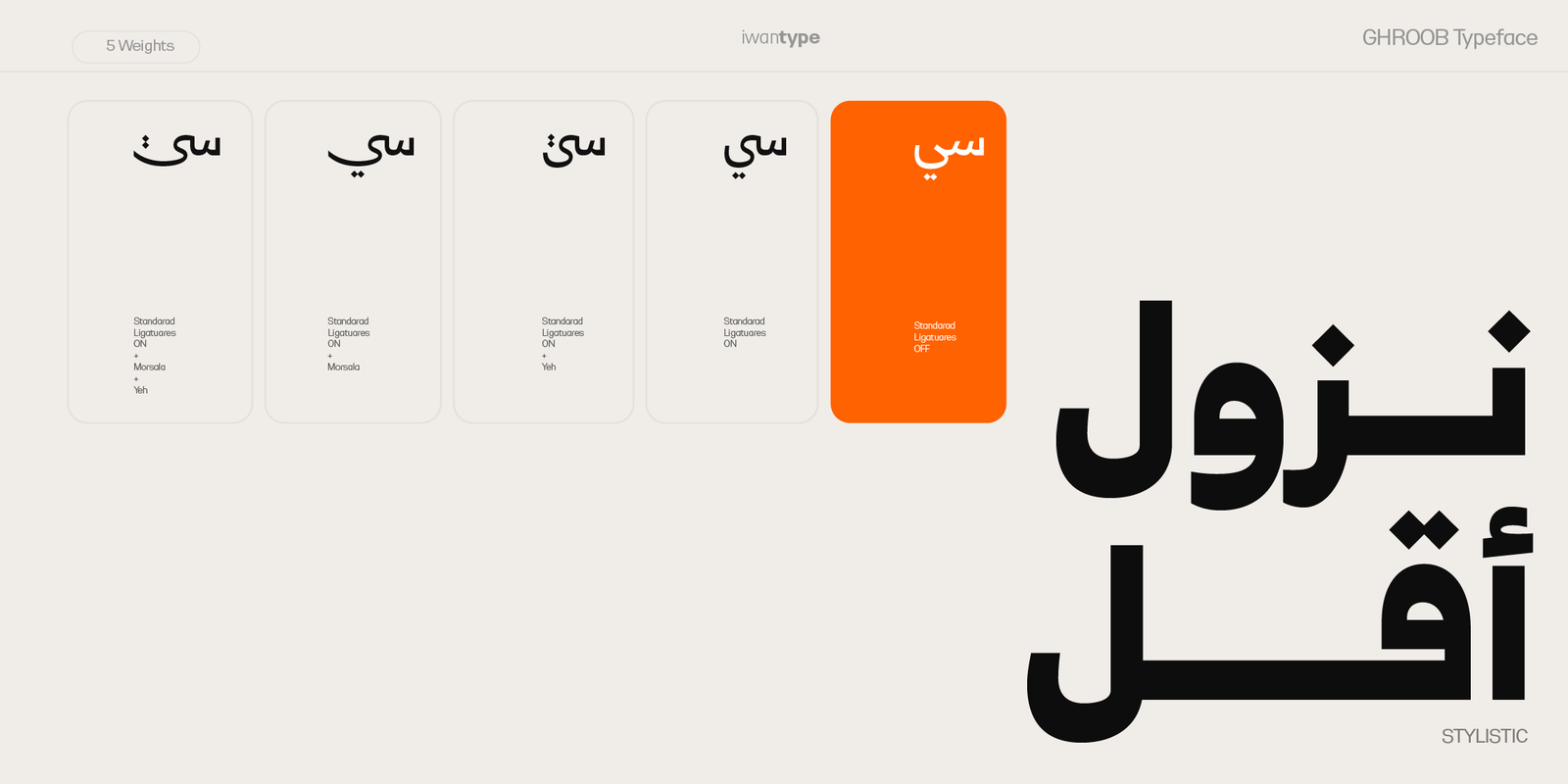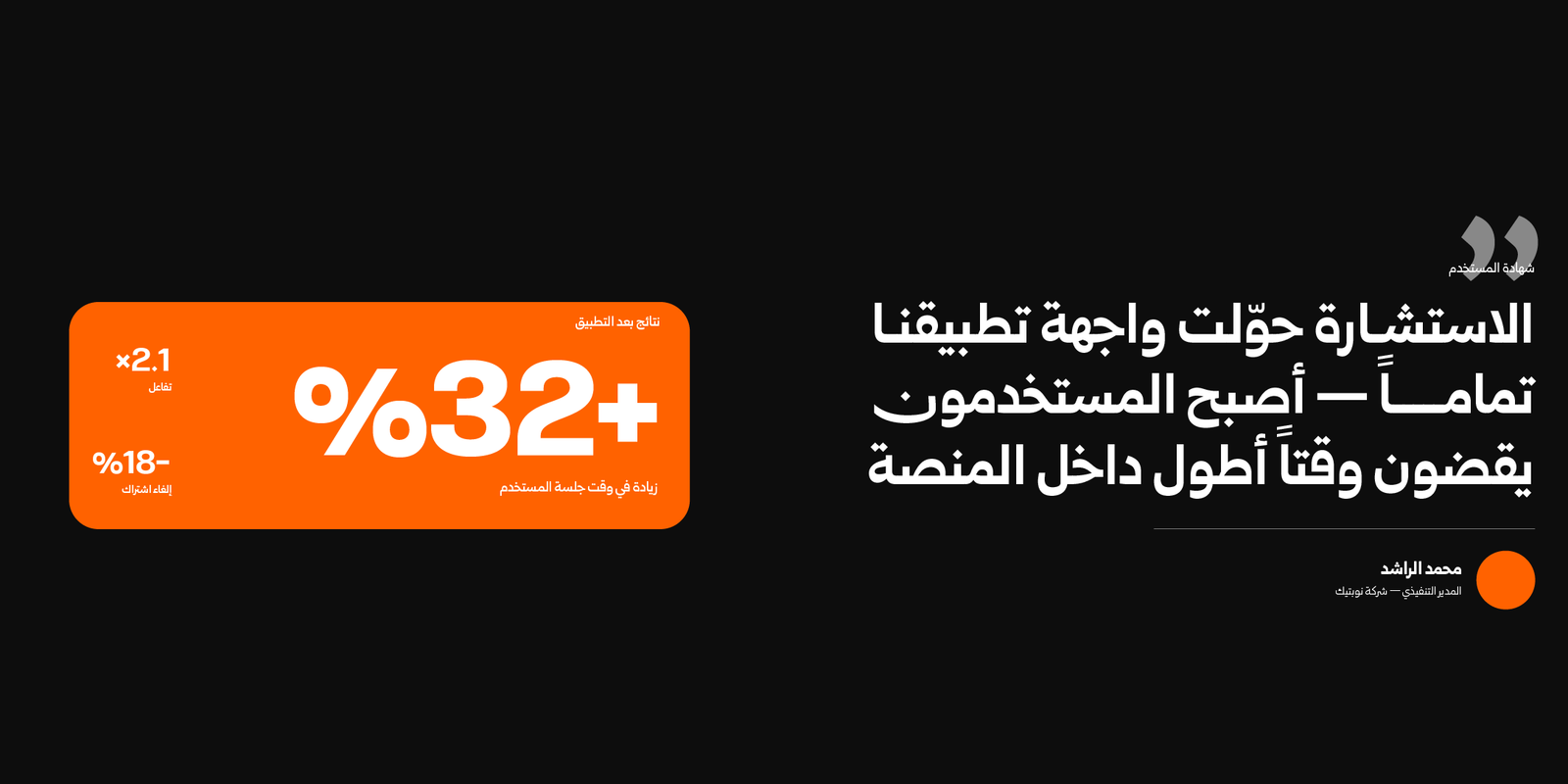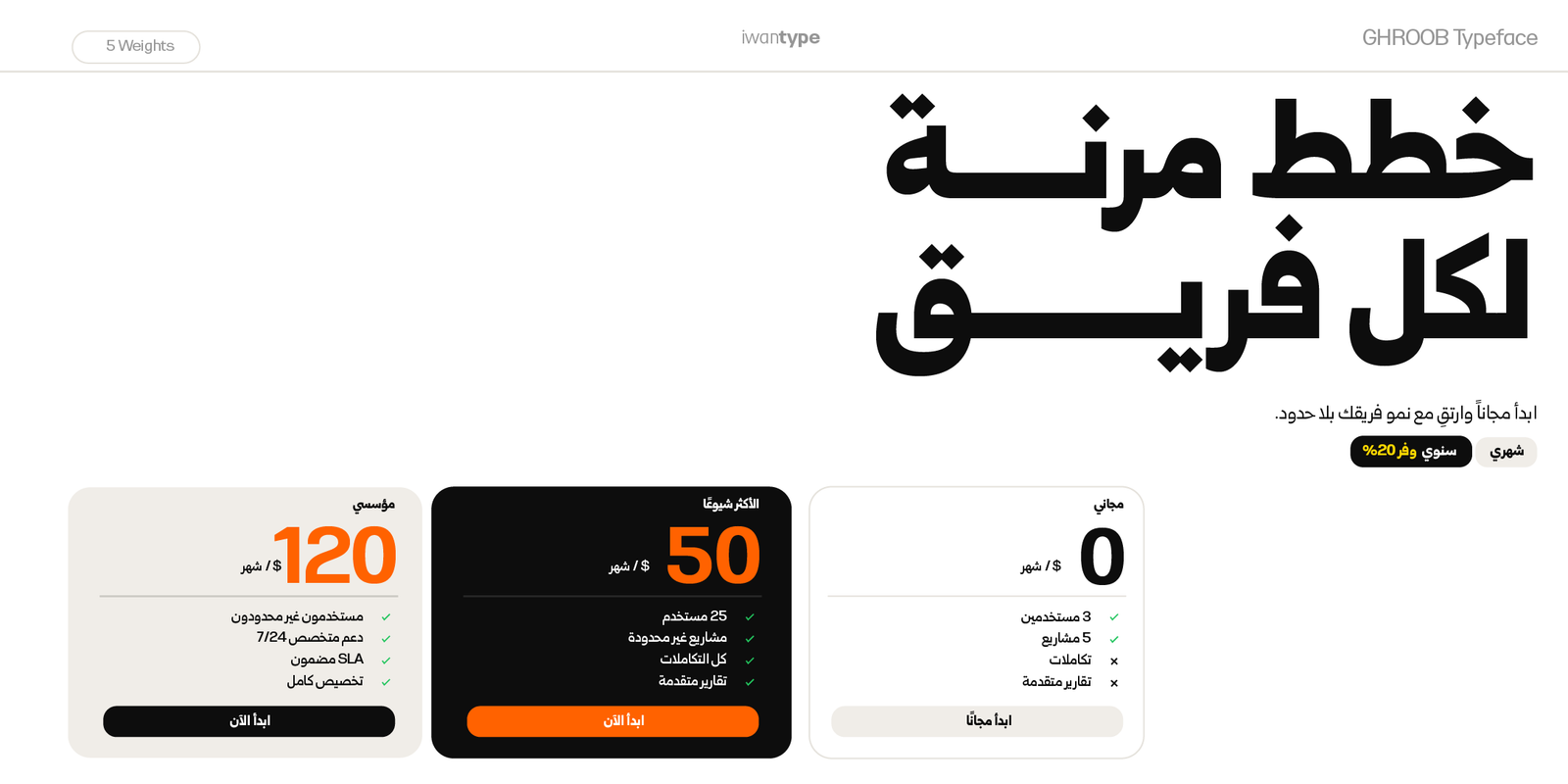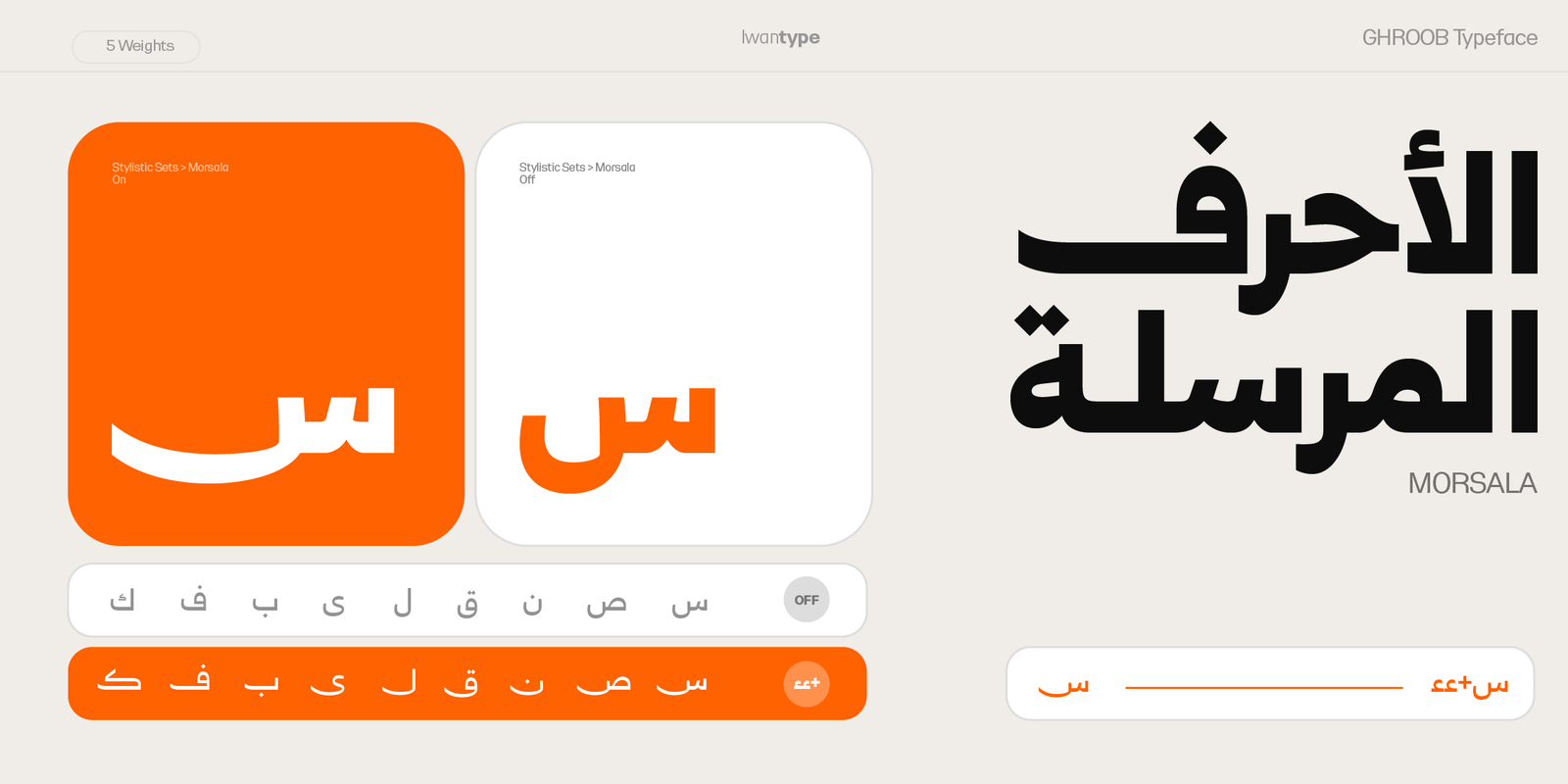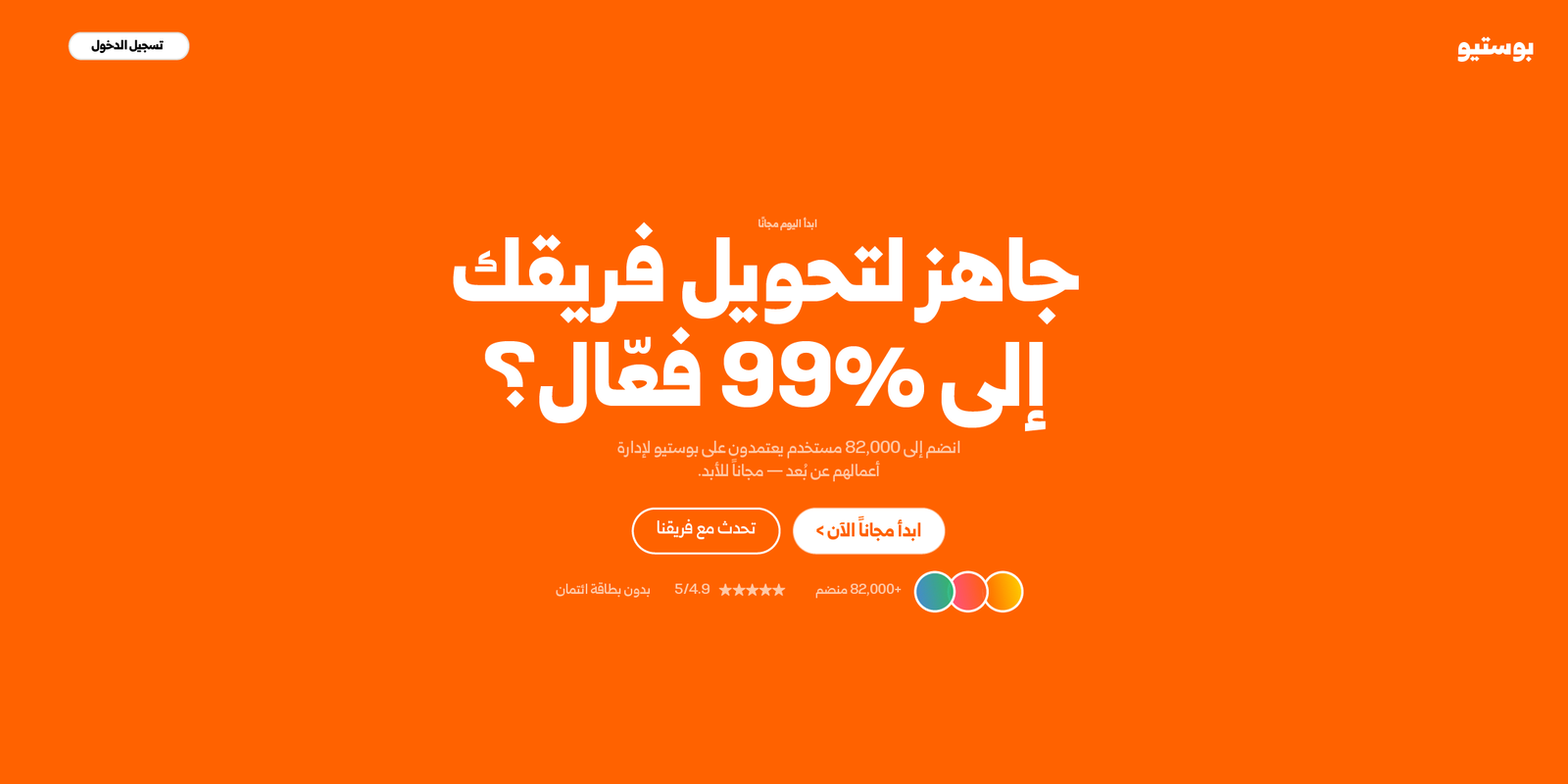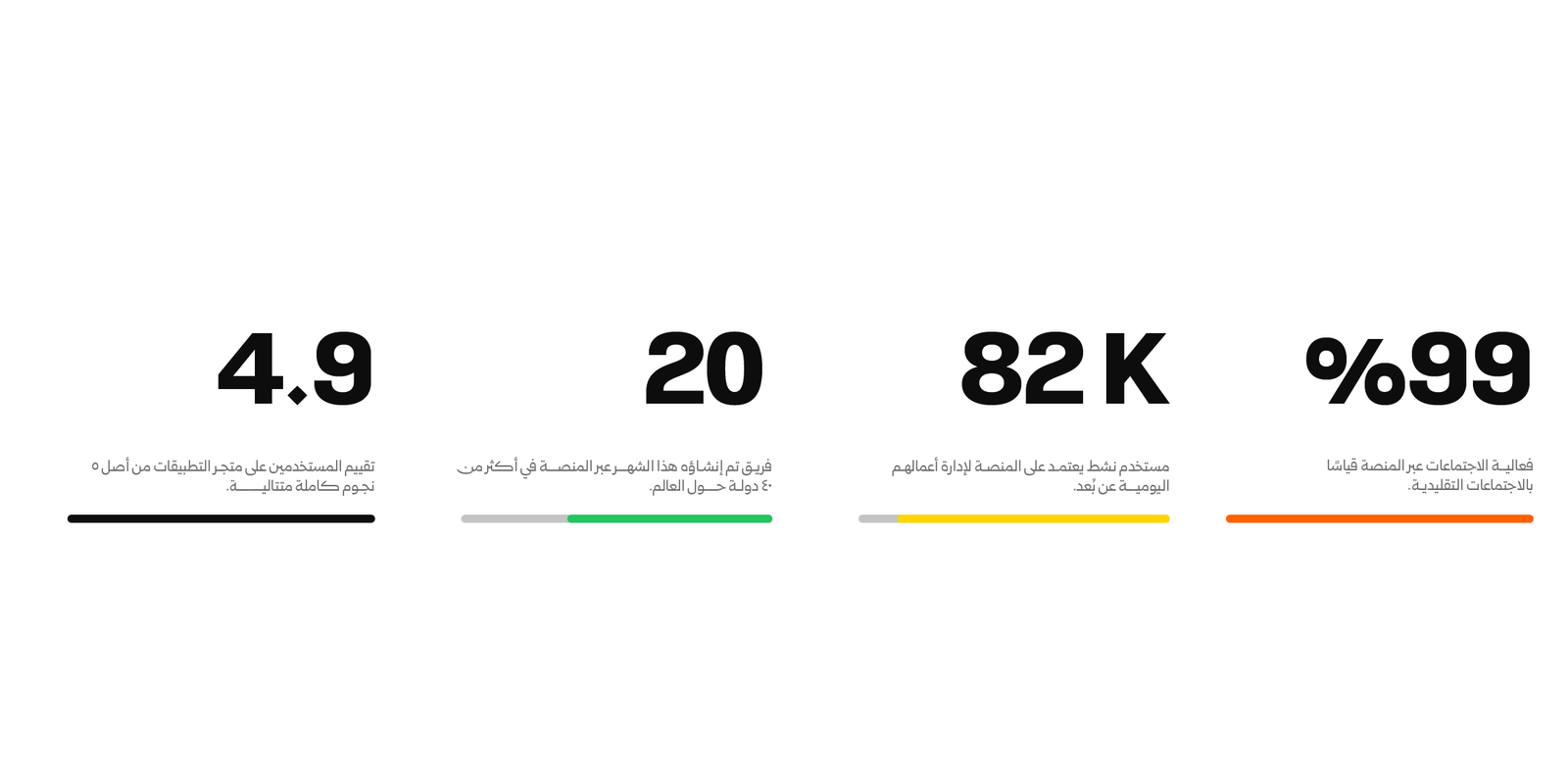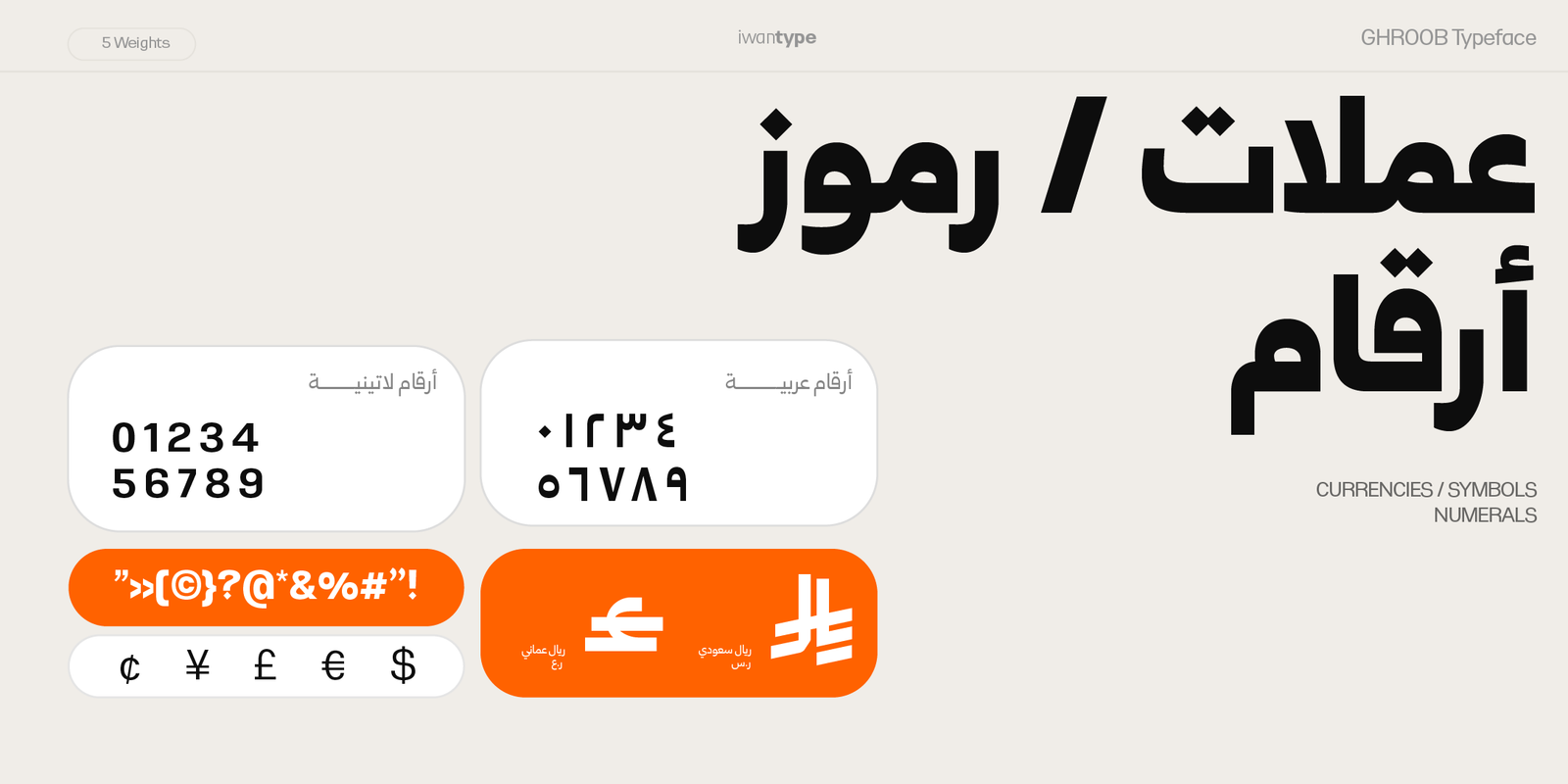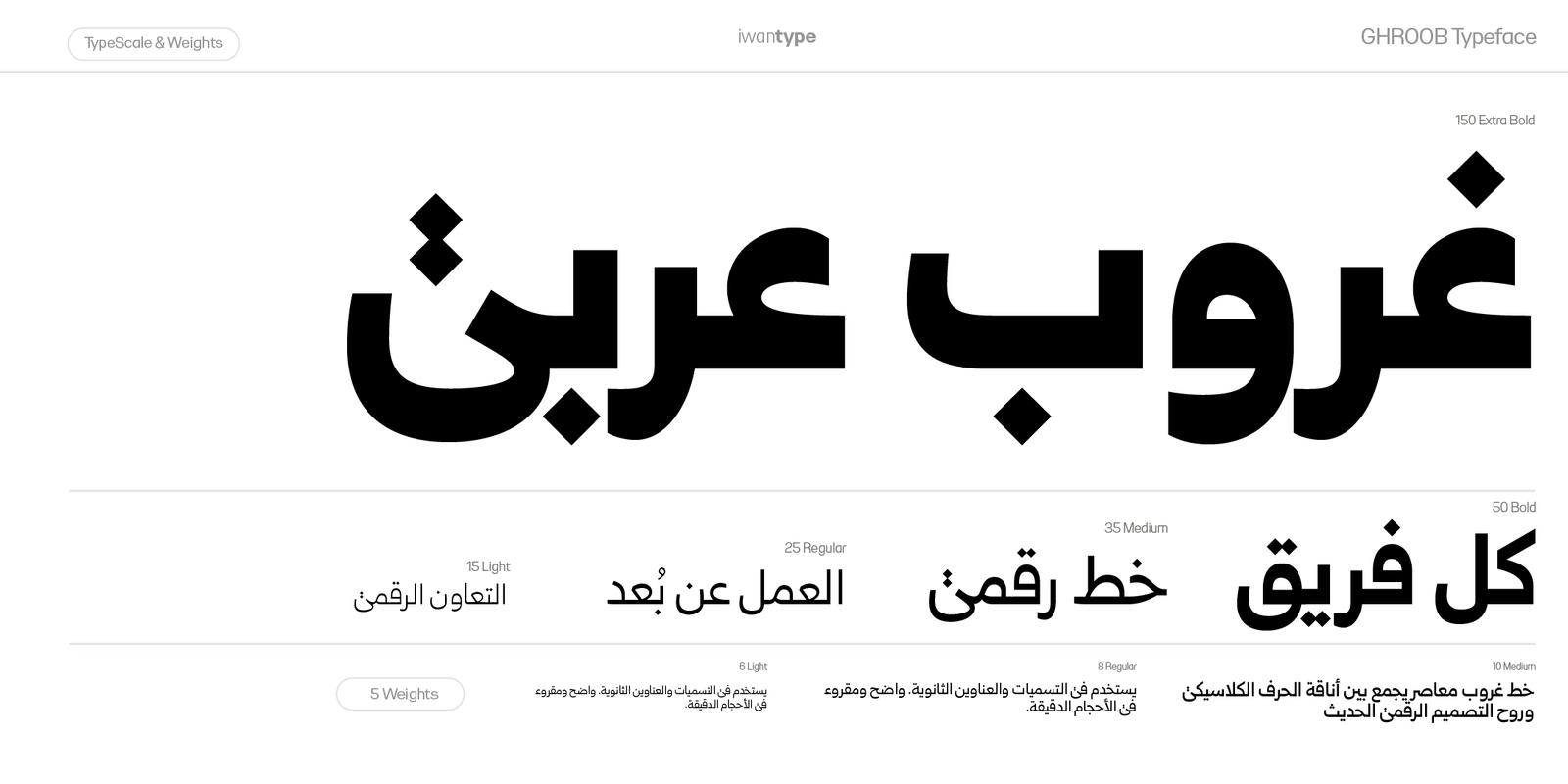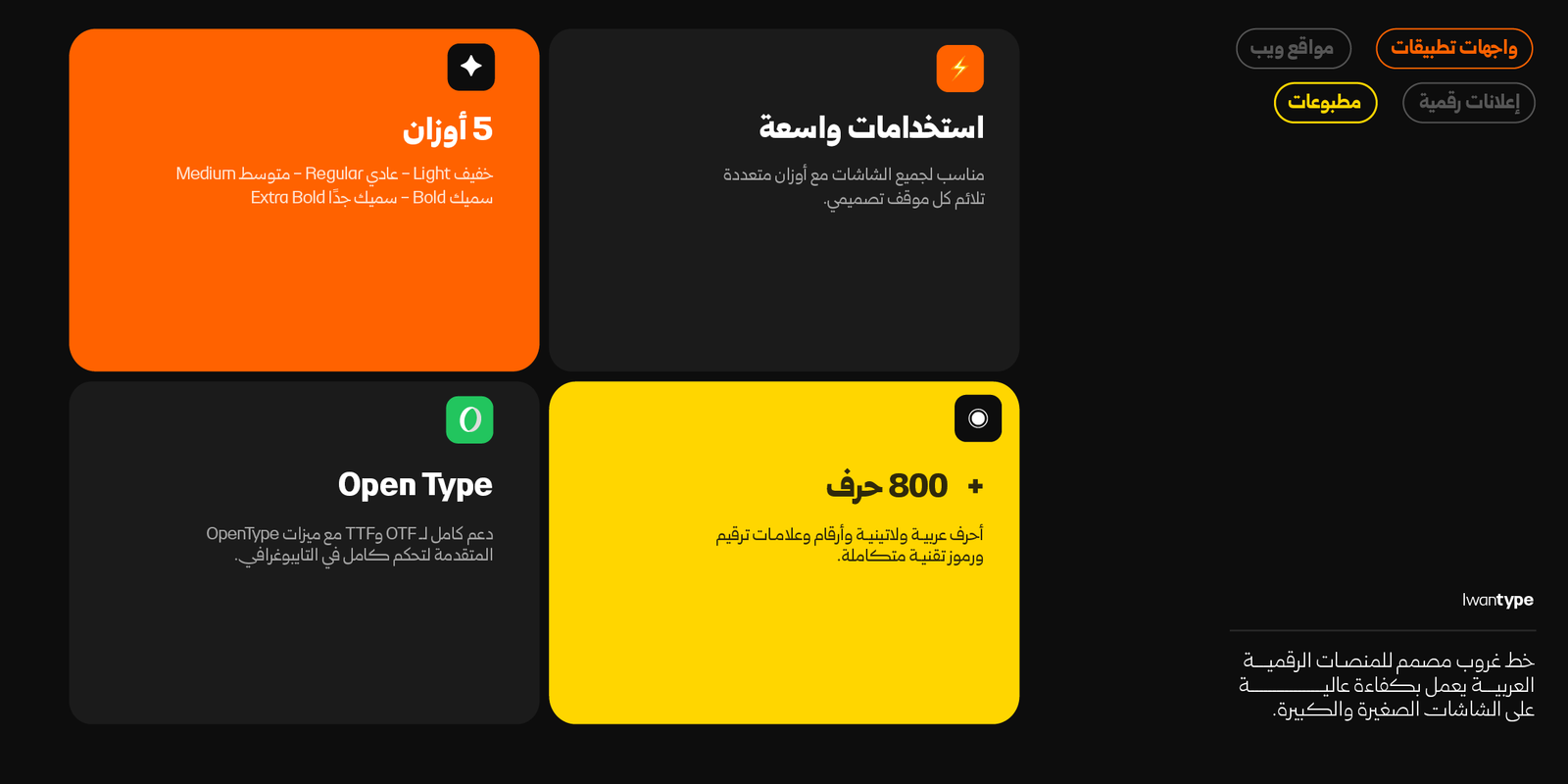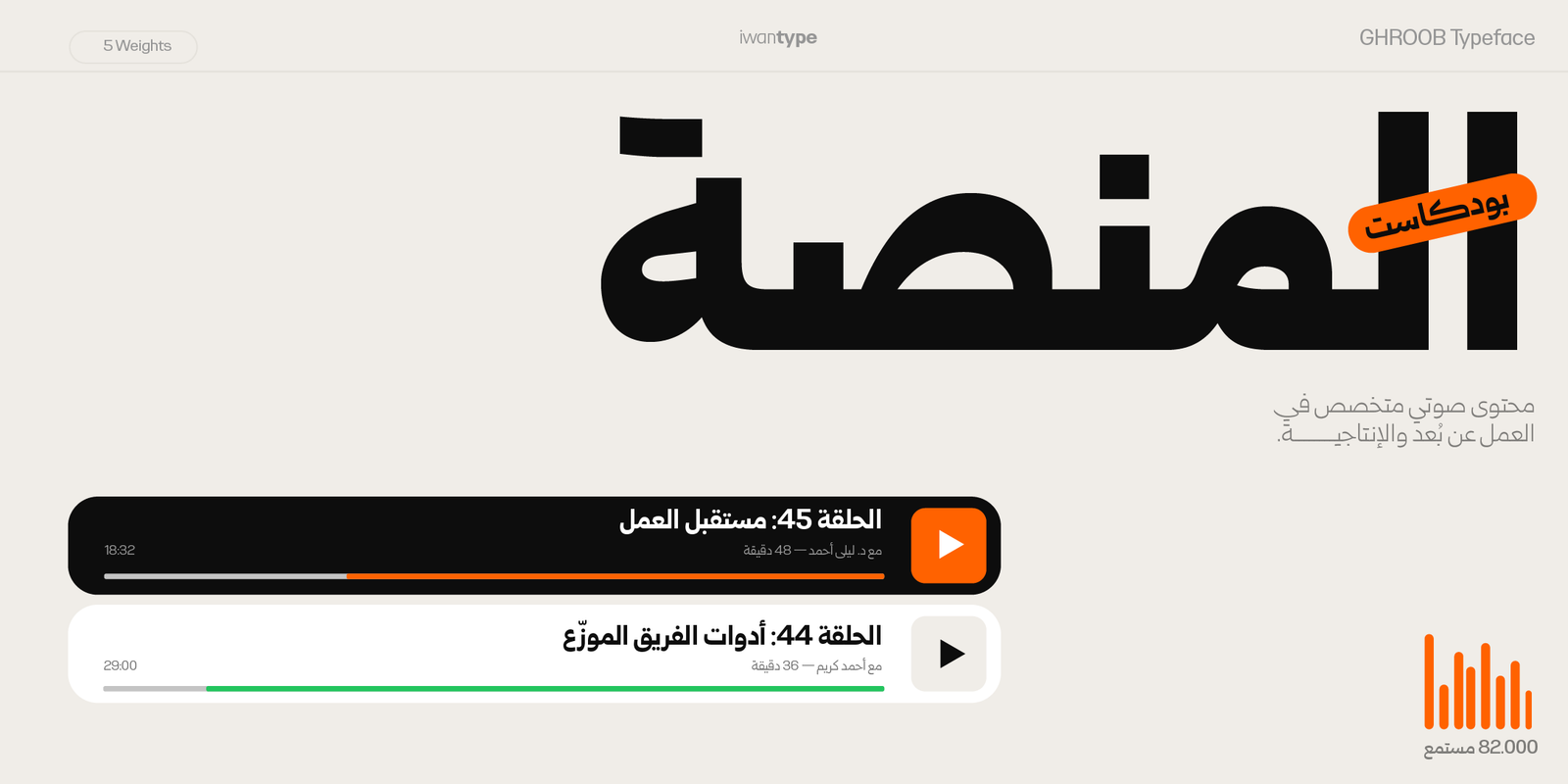
خط غروب – خط نسخ – Ghroob Arabic typeface
خط غروب العربي الطباعي – خط نسخ – Ghroob Arabic typeface
هو خط عربي فريد ومتميز، مستوحى من خط النسخ،يتميز بتصميم بسيط وانيق. ويمكن استخدامه في تصميم الجرافيك، والكتابة المطبوعة، والويب، والتطبيقات المحمولة.
مميزات خط غروب الطباعي:
- تصميم بسيط وأنيق: يجمع الخط بين البساطة والجمالية التقليدية لخط النسخ، مما يجعله مناسبًا لمختلف أنواع التصميمات.
- مزايـا OpenType: يتضمن الخط العديد من مزايا OpenType التي تضفي عليه مرونة وتنوعًا في الاستخدام، مثل:
- الحروف المرسلة: (تُفعَّل بإضافة “ءء” بعد الحرف)
- حرف ياء بنزول أقل: يقلل من نزول السطر، مما يعزز من انتظام النصوص.
- النقطة المستطيلة البديلة: توفر تنوعًا وجاذبية بصرية إضافية للنصوص.
- الحروف المركبة: تسهم في تحسين المظهر العام للنص وتزيد من سلاسته.
- يدعم رمز الريال السعودي والريال العُماني ،ويتم تفعيلهما تلقائيًا عند كتابة الاختصارات: ر.س للريال السعودي ر.ع للريال العُماني
- توافر الأوزان: يأتي خط غروب الطباعي بخمسة أوزان مختلفة.
اللغات : العربية والإنجليزية